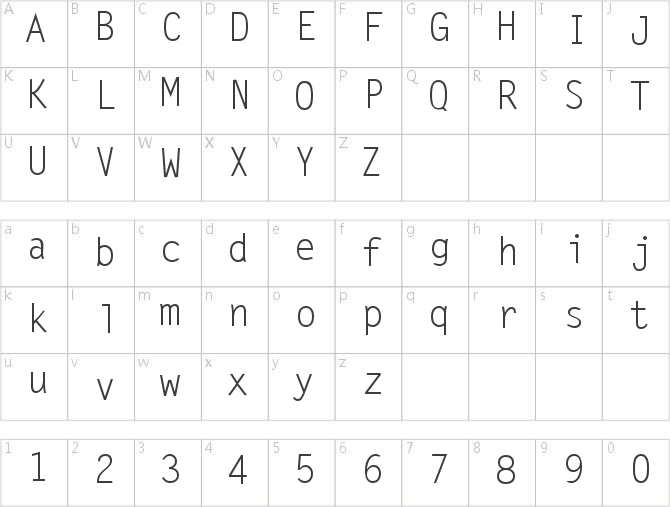
Letter-Gothic 詳情頁
字體名稱: Letter-
Letter-Gothic
Letter-Gothic介紹
Letter-Gothic字體字庫是一款讓人賞心悅目、百看不厭的英文字體,適合各類廣告和產(chǎn)品包裝設(shè)計應(yīng)用,字體大小0.04MB,格式為ttf字體,上傳用戶是瀨子,作者/版權(quán)方為未知